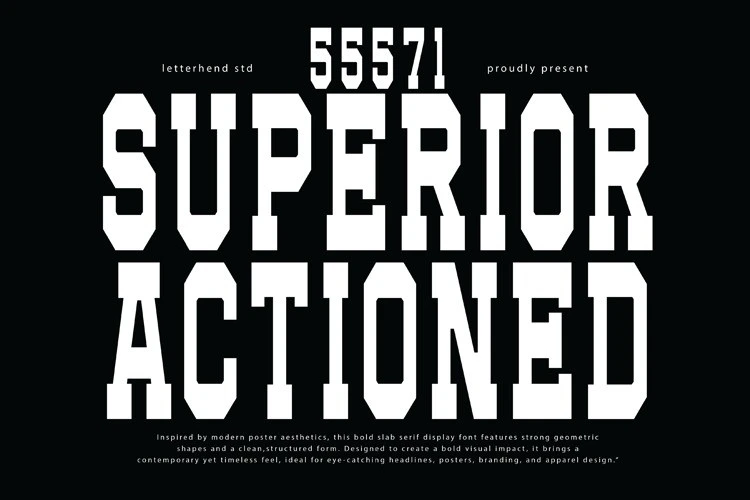
Superior Actioned Font
Superior Actioned Font gür ve kararlı bir şekilde geliyor—büyük, cesur blok serif biçimleriyle, gereksiz süsler olmadan afişe hazır bir vurgu. Harfler, basılmış metal gibi sağlam hissediliyor; kenarları keskin, yapısı ise temiz. Güçlü, sportif ve vintage-endüstriyel bir hava yayıyor.
Superior Actioned Font, gür ve kararlı—büyük, kalın slab-serif şekilleriyle birlikte, gereksiz süslemeye yer yok; afişe hazır bir vurgu sunuyor. Harfler, basılı metal gibi sağlam hissediliyor; kenarları keskin ama yapısı temiz, güçlü, sportif ve vintage-endüstriyel bir hava yayıyor.